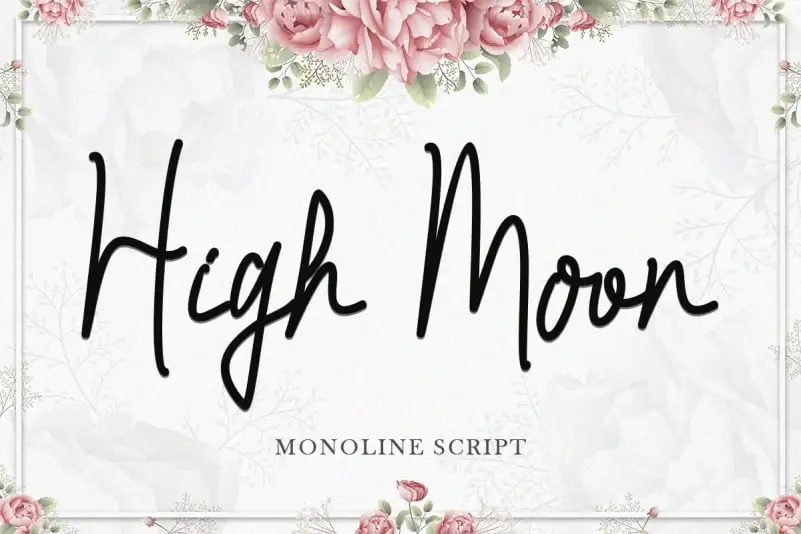
High Moon Handwritten Font – Download Grátis
A fonte “High Moon Handwritten Font” é uma elegante escolha para quem busca uma autêntica sensação de personalização. Desenhada pelo designer Yoga Letter, essa fonte possui um estilo monoline script que a torna única e encantadora, proposta para uso em diversas ocasiões. É perfeita para se destacar nos aniversários, noivas, eventos da primavera ou do verão, eco-dias, escrita de cartas pessoais, promoções de produtos, atualizações nas redes sociais e criação de logotipos. O design é simples e intuitivo, fazendo com que seja fácil de integrar em um grande número de projetos, desde banners até prints e adesivos para outdoors. Ideal tanto para designers profissionais quanto para aqueles que desejam dar uma personalidade autêntica a seus trabalhos domésticos. Seja você criando cartas familiares, lançando novidades em sua empresa ou simplesmente anotando suas observações diárias, a “High Moon Handwritten Font” se encaixa perfeitamente no seu universo de criações.